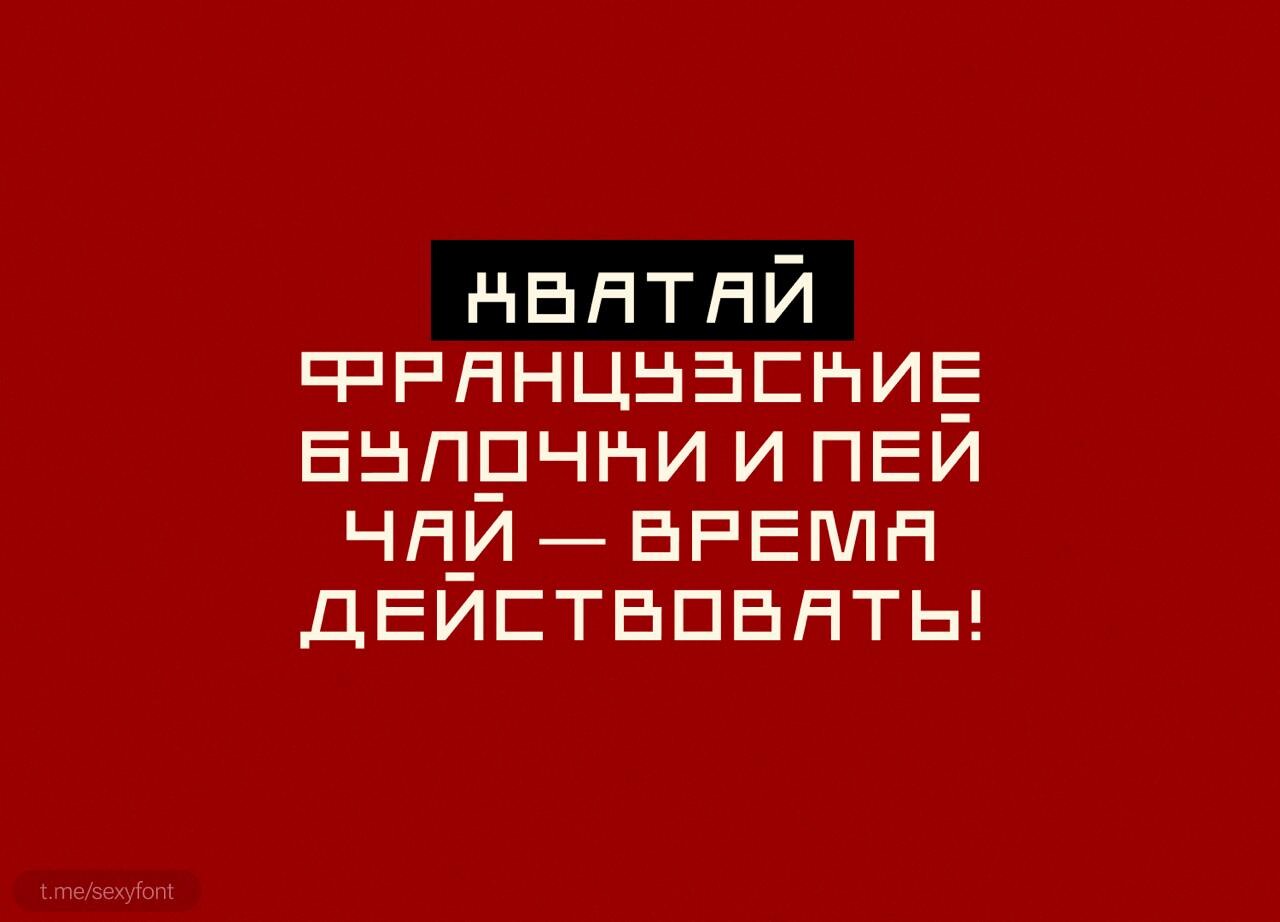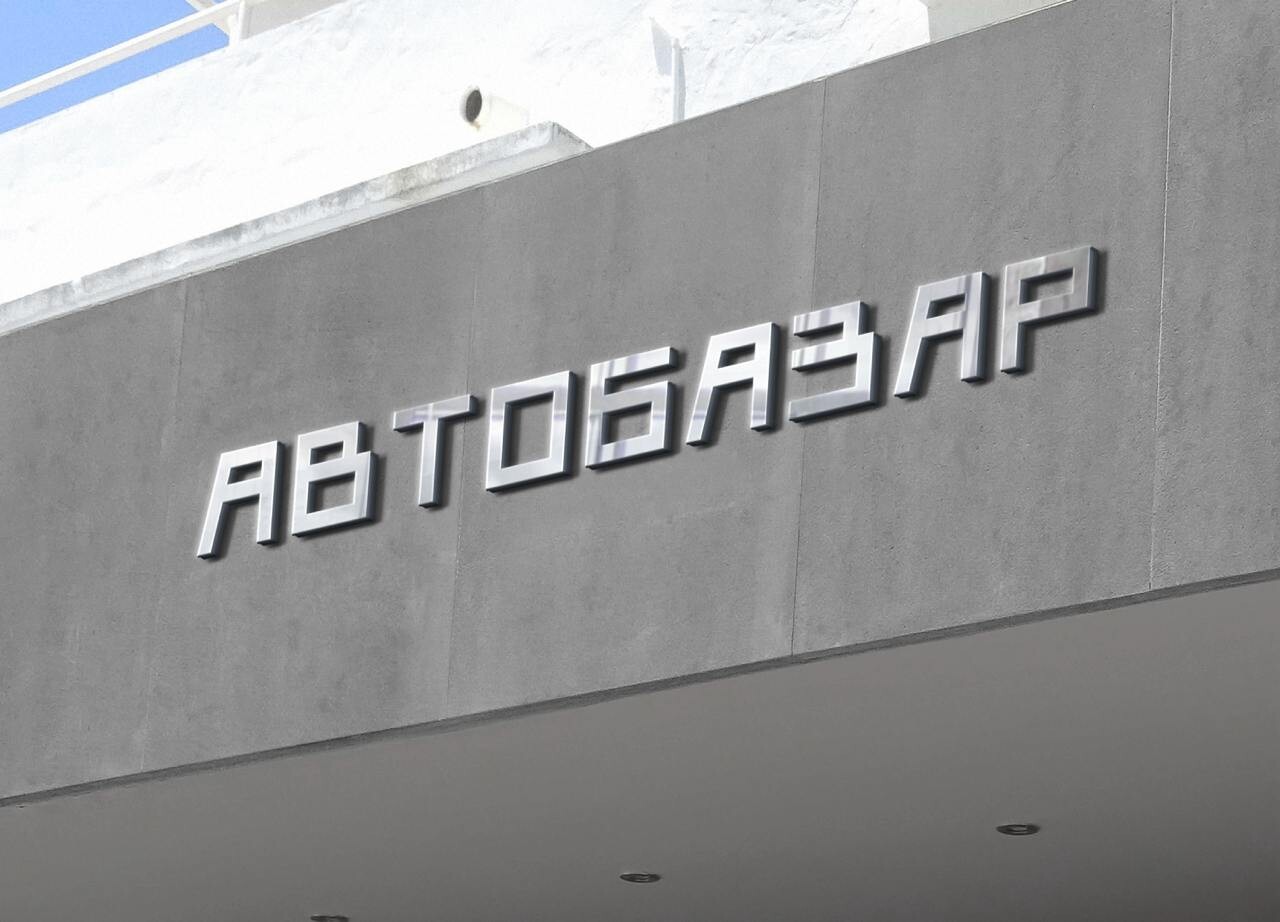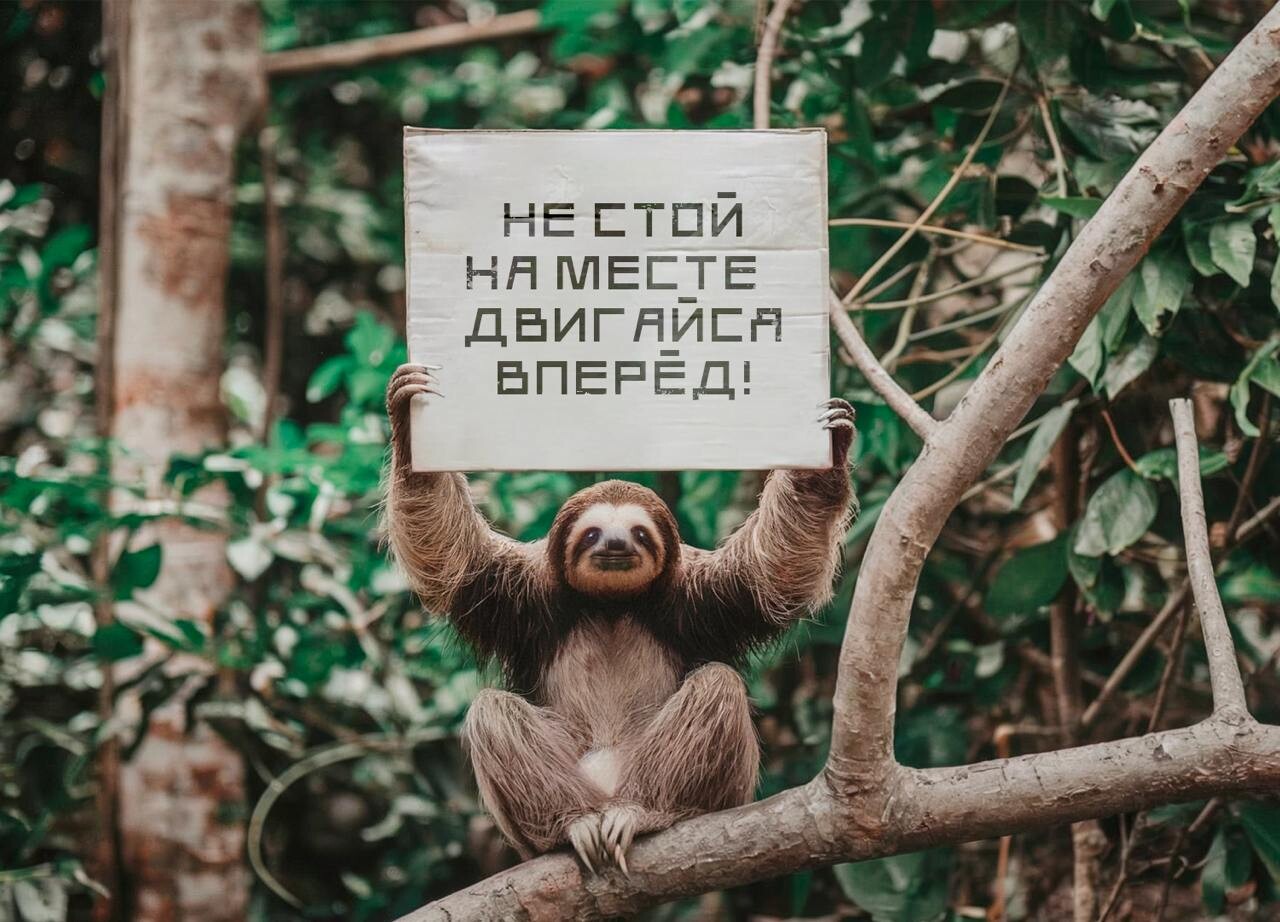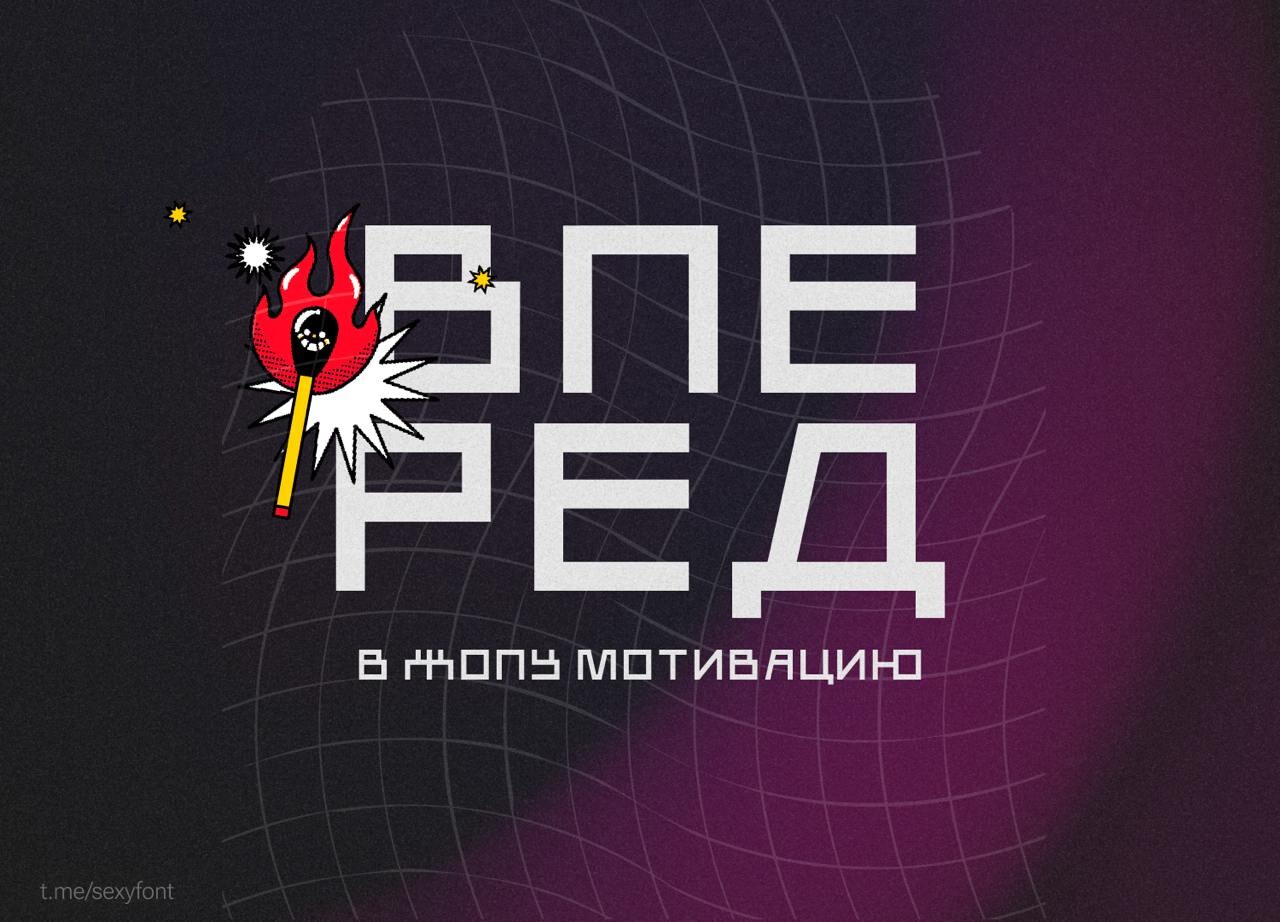
Шрифт Активистка: прямая речь в геометрических формах ✍️👍
А что, если шрифт не станет кружить вокруг да около, а скажет всё прямо и по делу? Получается Активистка - лаконичный прямоугольный шрифт, созданный для небольших заголовков. Никаких лишних завитушек. Только чёткость и характер. Неожиданно свежо, правда?
Авторский подход
Активистка - работа Алимы Сибгатуллиной. Это прямоугольный шрифт, который идеально подходит именно для компактных заголовков. Геометрия здесь работает на максимальную выразительность. Буквы стоят уверенно, словно в строю, но при этом сохраняют современную лёгкость.
Простота с силой
В Активистке всё подчинено прямоугольным формам. Нет округлостей, которые могли бы смягчить впечатление. Зато есть чёткие линии и строгий ритм. Такой шрифт не прячется за декором - он заявляет о себе прямо. И это его главная сила.
Где он уместен
Активистка особенно хороша именно в небольших заголовках. Социальные сети, инфографика, карточки товаров, короткие слоганы - везде, где пространство ограничено, а внимание нужно привлечь быстро.
Мысль напоследок
Иногда самое сильное высказывание - это то, которое сказано без лишних слов. Активистка напоминает об этом: прямота может быть по-настоящему элегантной. И в этом её тихая, но уверенная сила. ✨